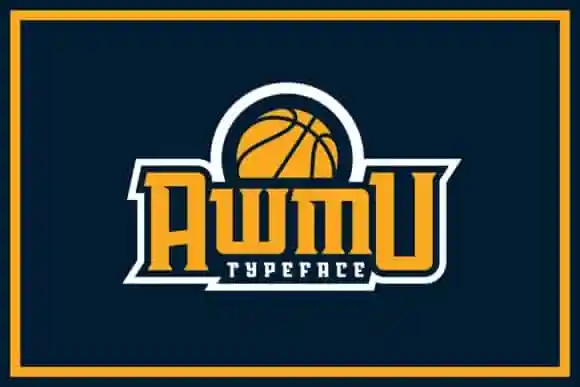
Awmu Display Font – Fonte Grátis
Awmu Display Font
Descubra a perfeição geométrica de Awmu Display Font no nosso catálogo. Esta fonte é tão versátil quanto sofisticada, sua beleza está em cada detalhe. Geométrica e elegante, Awmu possui um ajuste entrelinhado que torna seu uso incomplexo e prazeroso. O designer dickysyafaat criou uma opção única para o mundo da design gráfico, um font de display atraente e repleto de possibilidades. Use Awmu para criar designs impressionantes e não hesite em adicionar personalidade aos seus projetos com seu estilo único e arrasador. Adquira Awmu Display Font agora e transforme suas ideias em realidade!